Todos los que trabajamos en la amplia industria creativa, sabemos perfectamente de la basta y enorme cantidad de tipografías que podemos encontrar en Internet. El uso correcto de tipografías hará que nuestras composiciones tengan la legibilidad adecuada, el equilibrio y estética perfectos para destacar sobre la media.
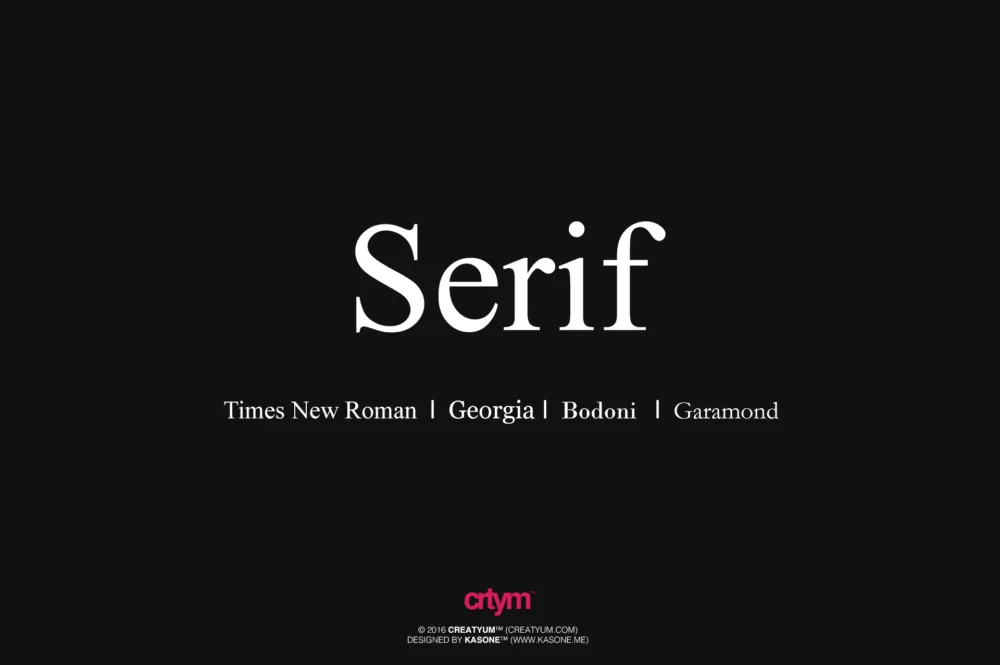
Las fuentes tipográficas del tipo serif, por lo general se asocian con aspectos profesionales, con la confianza y sobre todo con la seriedad. Es muy utilizada para eventos y aspectos corporativos.
Algunas de las fuentes serif más usadas son:
Times New Roman
Georgia
Bodoni
Garamond
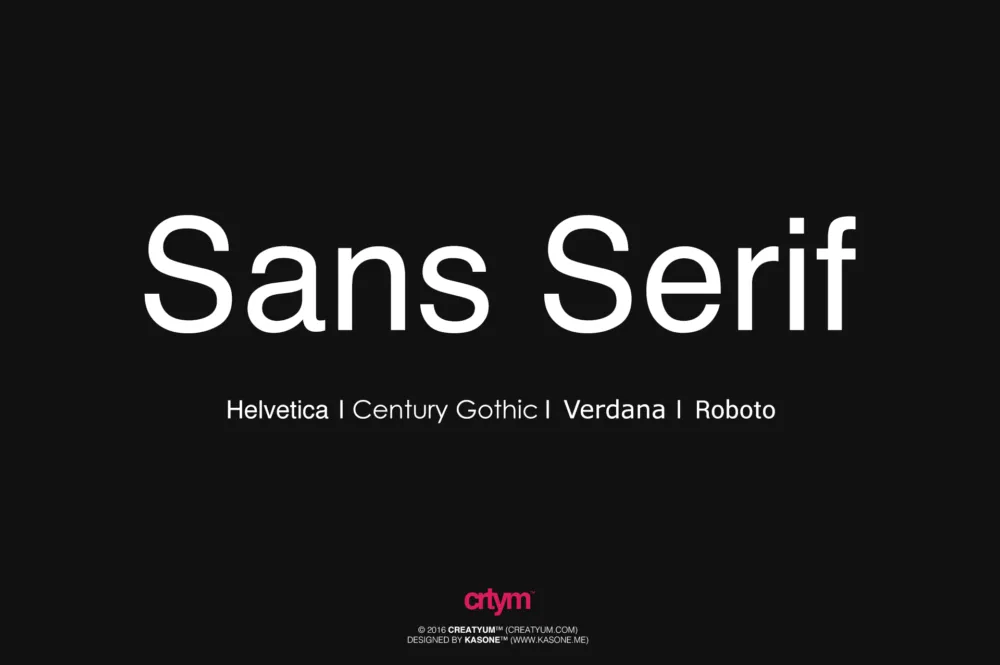
Las fuentes tipográficas del tipo sans serif, por lo general se asocian con cosas modernas, con la limpieza y con la estabilidad. Es muy utilizada para presentaciones de diapositivas y contenidos digitales.
Algunas de las fuentes sans serif más usadas son:
Helvetica
Century Gothic
Verdana
Roboto
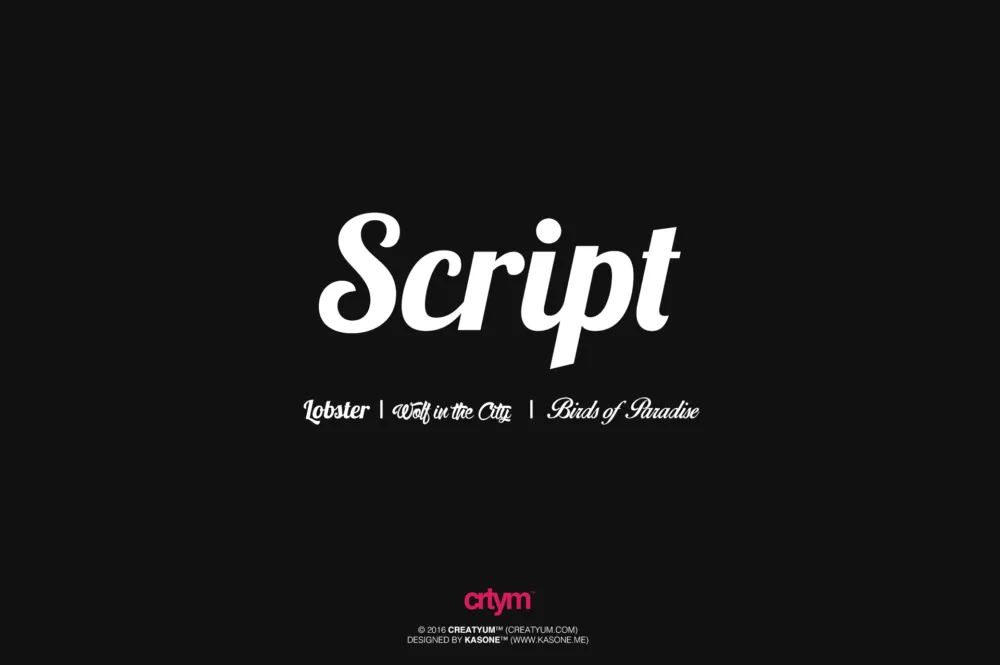
Las fuentes tipográficas del tipo script, por lo general se asocian con la elegancia, amabilidad, exclusividad; también se relacionan con la feminidad y la creatividad. Es muy utilizada para tarjetas de invitación para eventos (como bodas o bautizos), en diplomas o documentos.
Algunas de las fuentes script más usadas son:
Lobster
Wolf in the City
Birds of Paradise
Puedes hacer combinación de fuentes serif con fuentes sans serif. También, puedes hacer una combinación de script con sans serif. Si vas a hacer uso de combinaciones, procura utilizar sólo dos fuentes tipográficas como máximo.
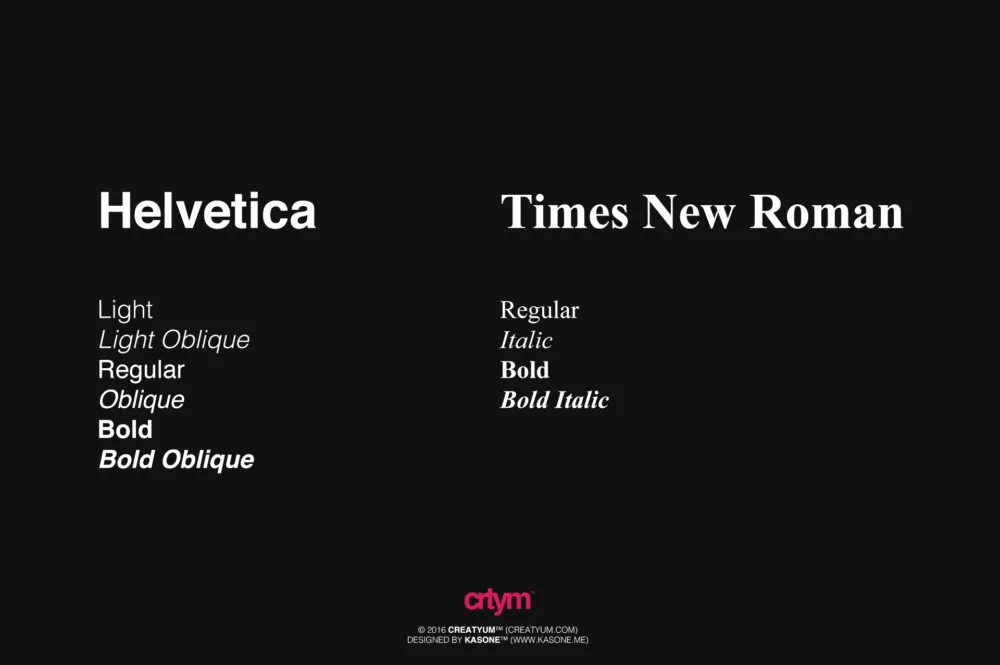
Otra forma adecuada de utilizar una tipografía, es con las variantes de éstas, ya que a veces no es necesario recurrir a otros estilos ya que nuestras tipografías poseen variantes a parte de la regular como pueden ser bold, italic, oblique, medium o black.
Un aspecto fundamental e importante en toda composición es: el espacio y la alineación de los elementos, los cuales incluyen los textos y títulos. Procura distribuir todo de una forma bastante equilibrada y ordenada. También, no olvides que debe poder ser legible, por lo que no uses tamaños demasiado altos cómo 18pt a 24pt para un párrafo (aplica más en programas editoriales como InDesign o procesadores de texto como Word que en programas de mapas de bits como Photoshop o programas vectoriales como Illustrator), en su lugar, utilizar entre 12pt a 16pt (también depende del tipo de composición). Para párrafos más pequeños como pies de página, puedes usar entre 8pt a 10pt. Para los títulos puedes jugar entre 24pt a 72pt (pueden ser puntos más grandes dependiendo el tipo de composición que estés haciendo).